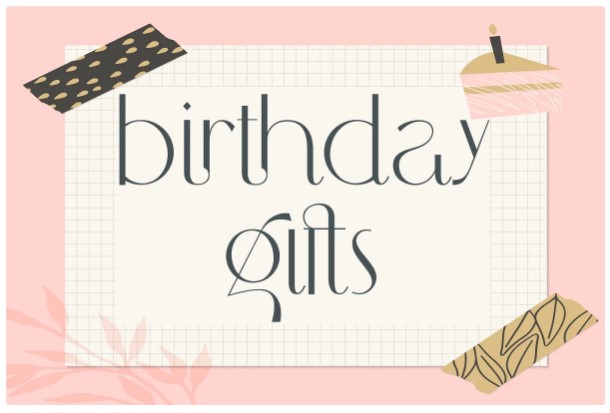
Представляем MCLASSIC FONT - элегантный современный шрифт sans serif, вдохновленный роскошными модными брендами.
Он потрясающе выглядит на дисплеях и легко читается в текстовом формате.
Существует две версии этого шрифта: REGULAR и ITALIC.
Его чистота и минимализм прекрасно подходят для логотипов, заголовков, плакатов, упаковки и многого другого!